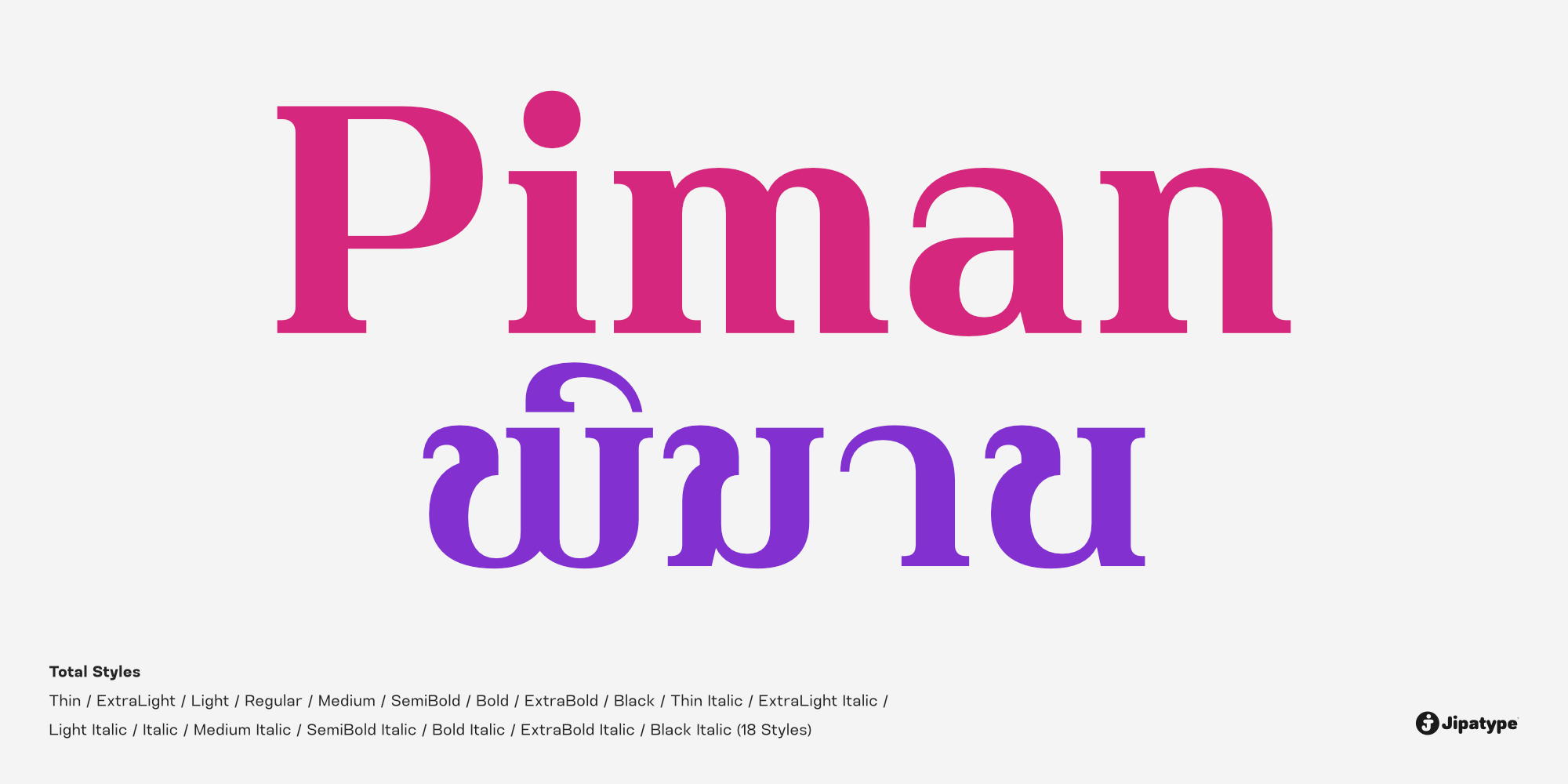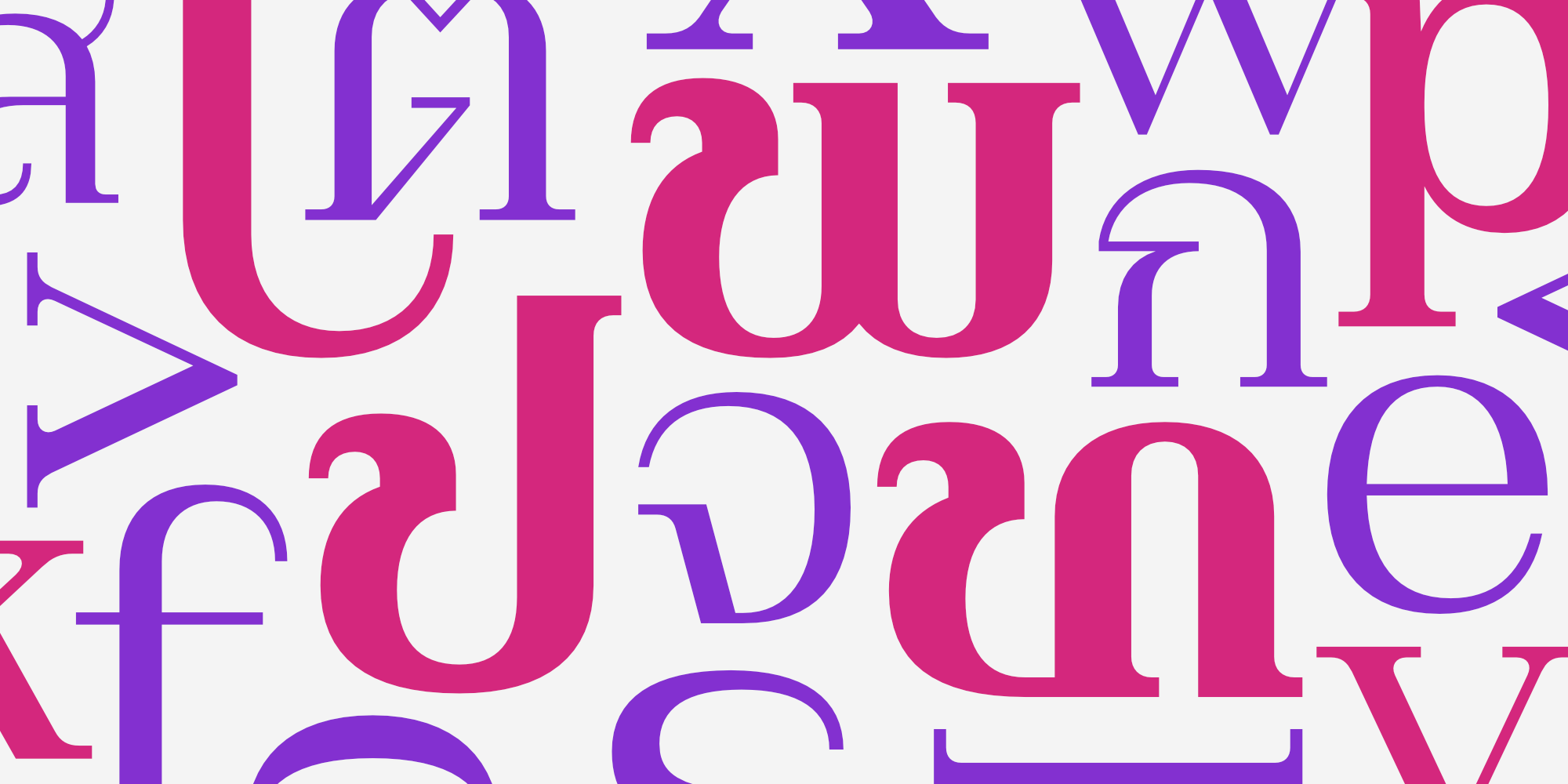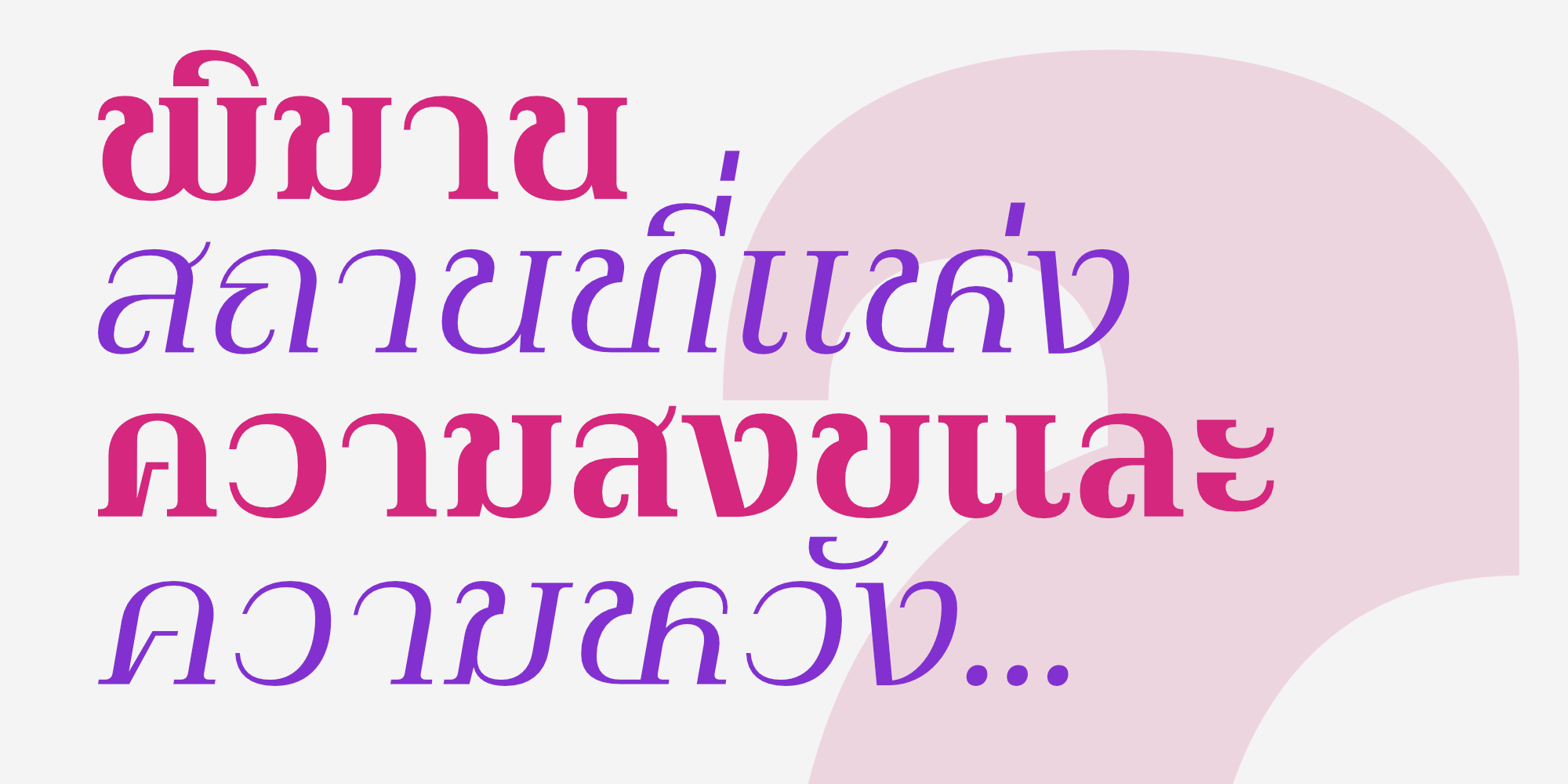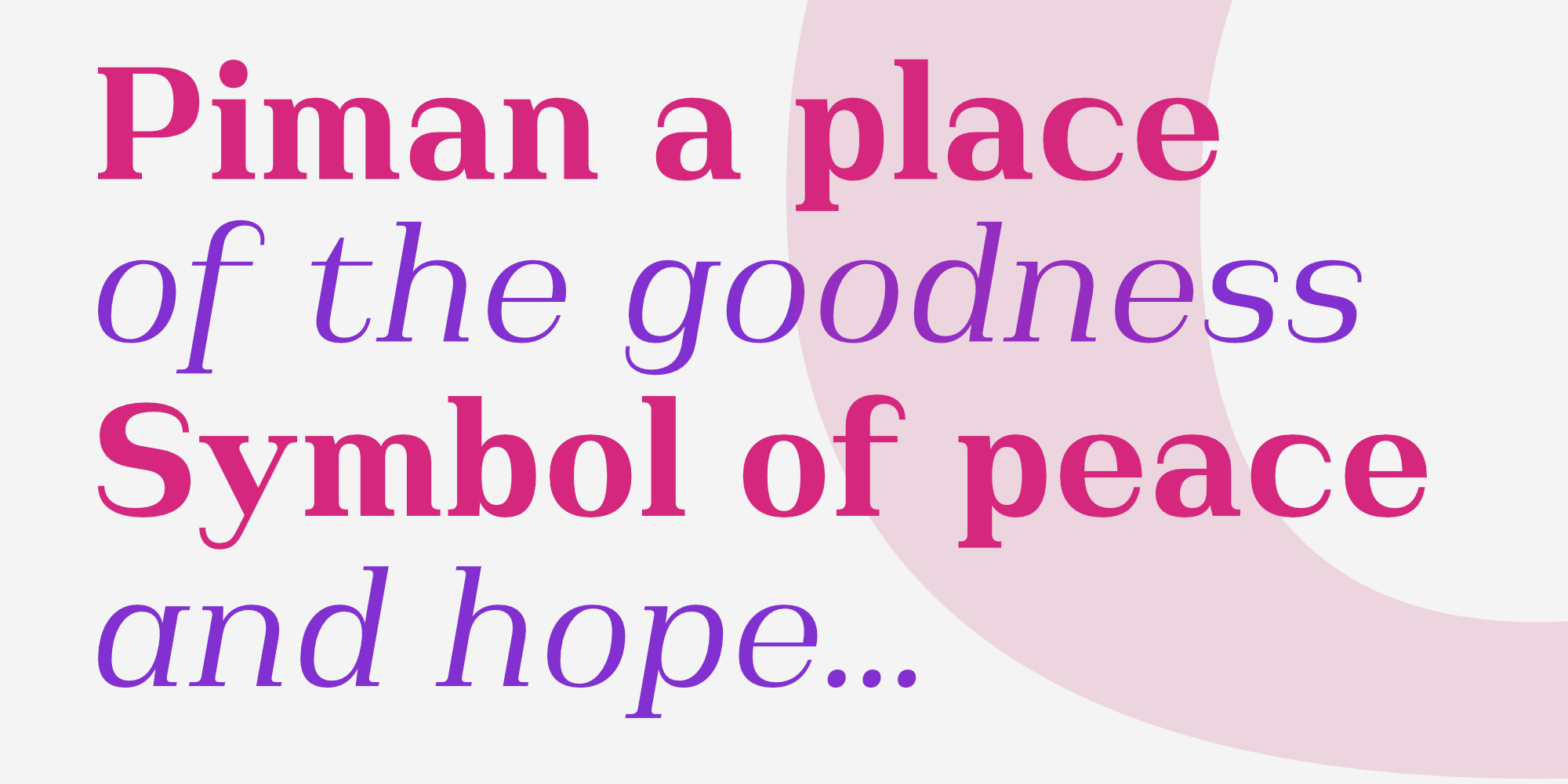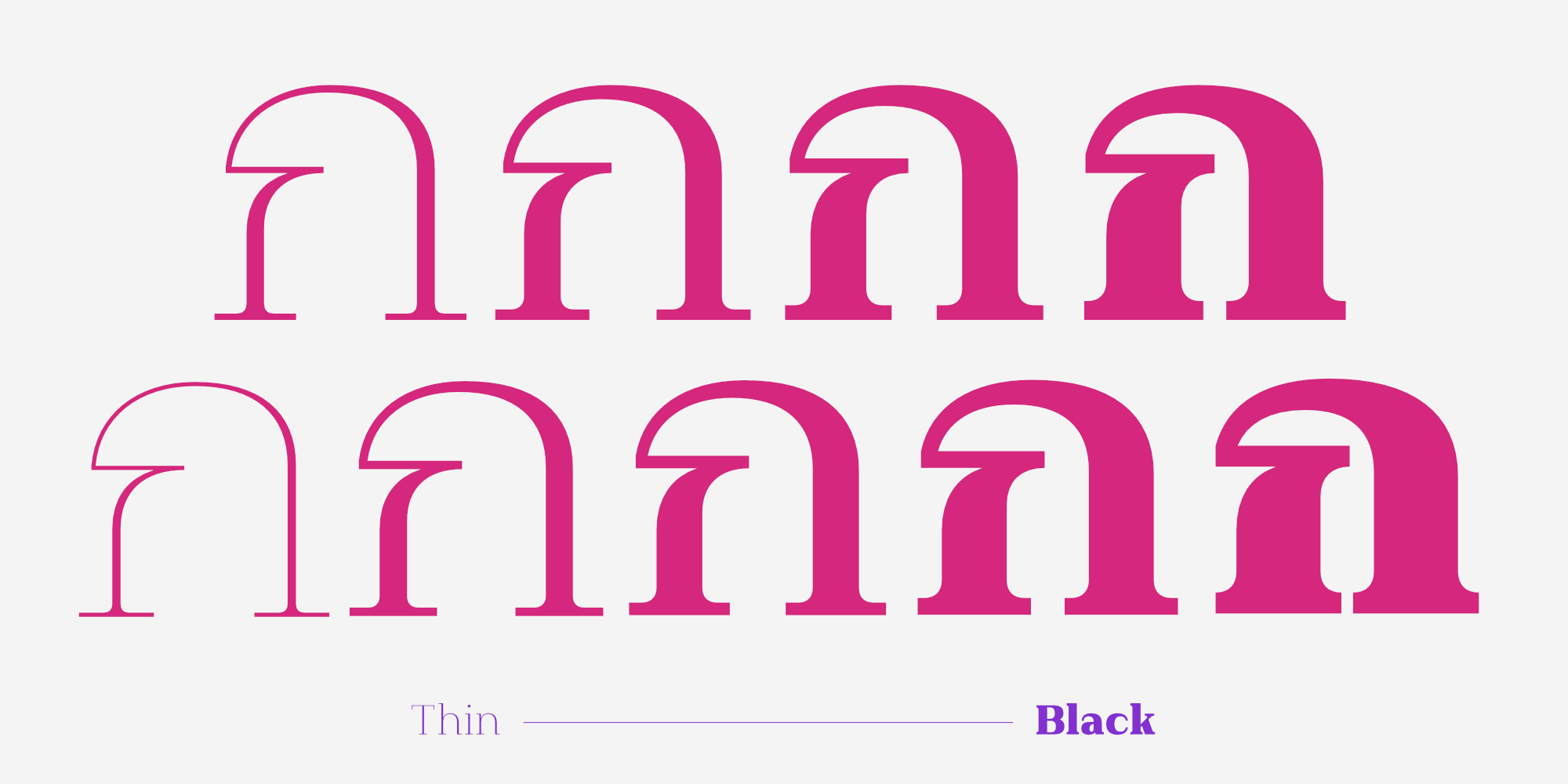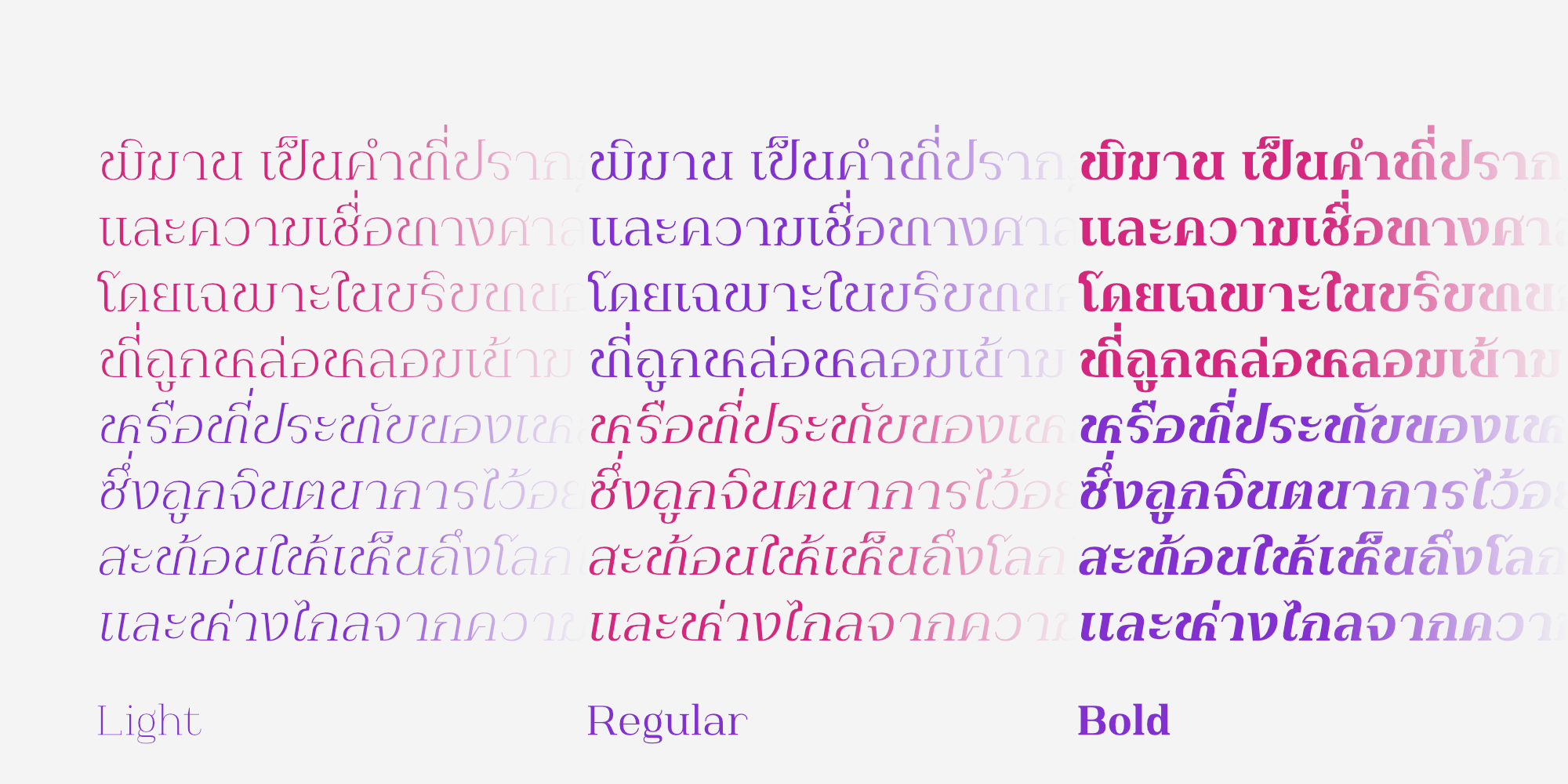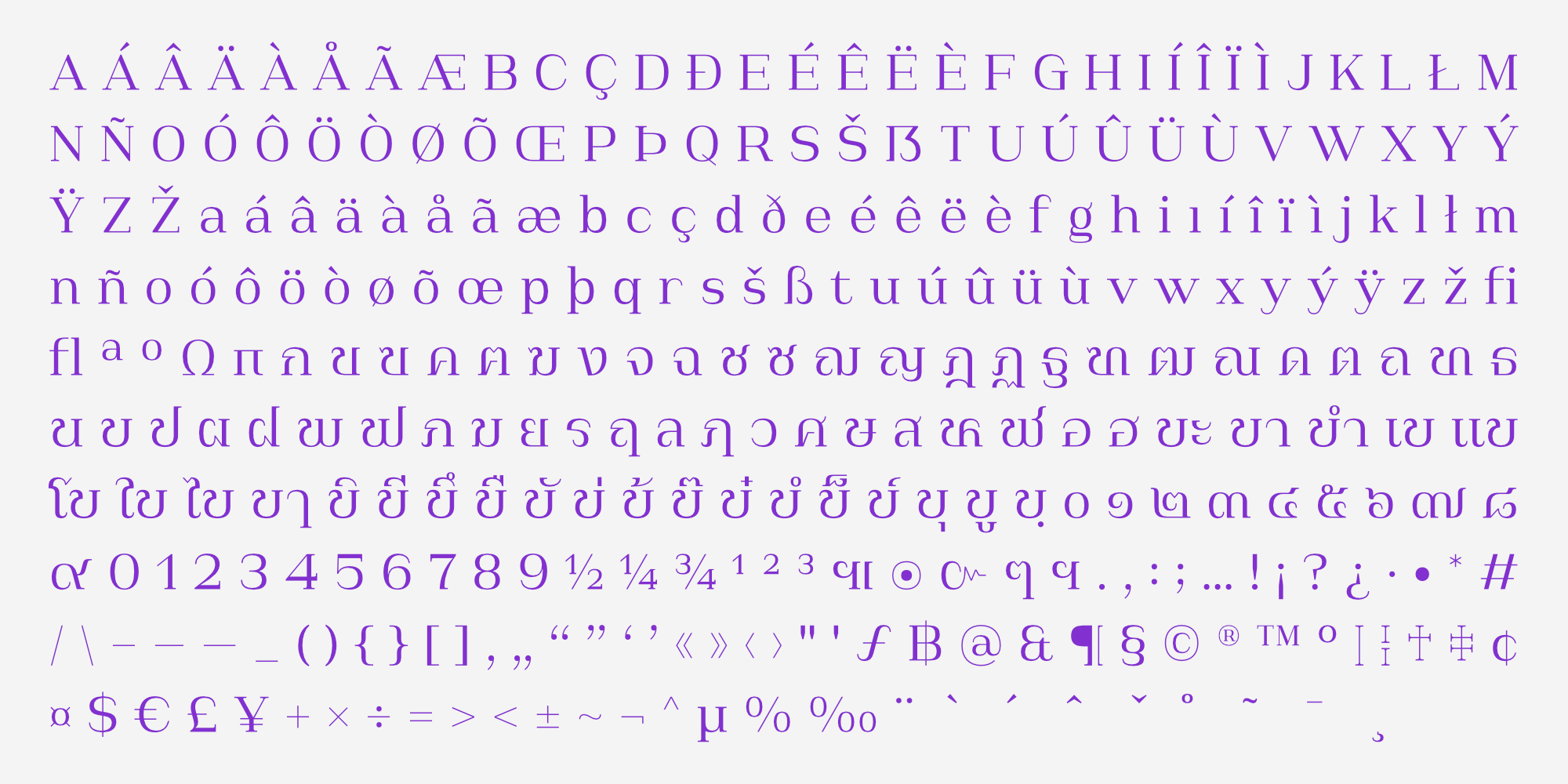
Piman คือแบบอักษรเซอริฟ (Serif) ที่ผสานความสง่างามแบบคลาสสิกเข้ากับรายละเอียดร่วมสมัยอย่างประณีต ตัวอักษรมีเอกลักษณ์ที่โดดเด่นด้วยโครงสร้างที่มั่นคง เส้นหนา–บางที่กลมกลืน และรูปทรงที่ให้อารมณ์หนักแน่นแต่ไม่แข็งกระด้าง
เหมาะสำหรับการใช้งานที่ต้องการความน่าเชื่อถือ ความหรูหรา และกลิ่นอายของความเป็นทางการ รองรับทั้งตัวอักษรไทย และละติน (Latin–1 Supplement) จึงสามารถใช้งานได้หลากหลายบริบท ไม่ว่าจะเป็นแบรนดิ้ง สิ่งพิมพ์ บรรณาธิการ บทความ หรือแม้แต่โปรเจกต์เชิงวัฒนธรรม
ออกแบบโดย : อานุภาพ ใจชำนาญ (Anupap Jaichumnan)